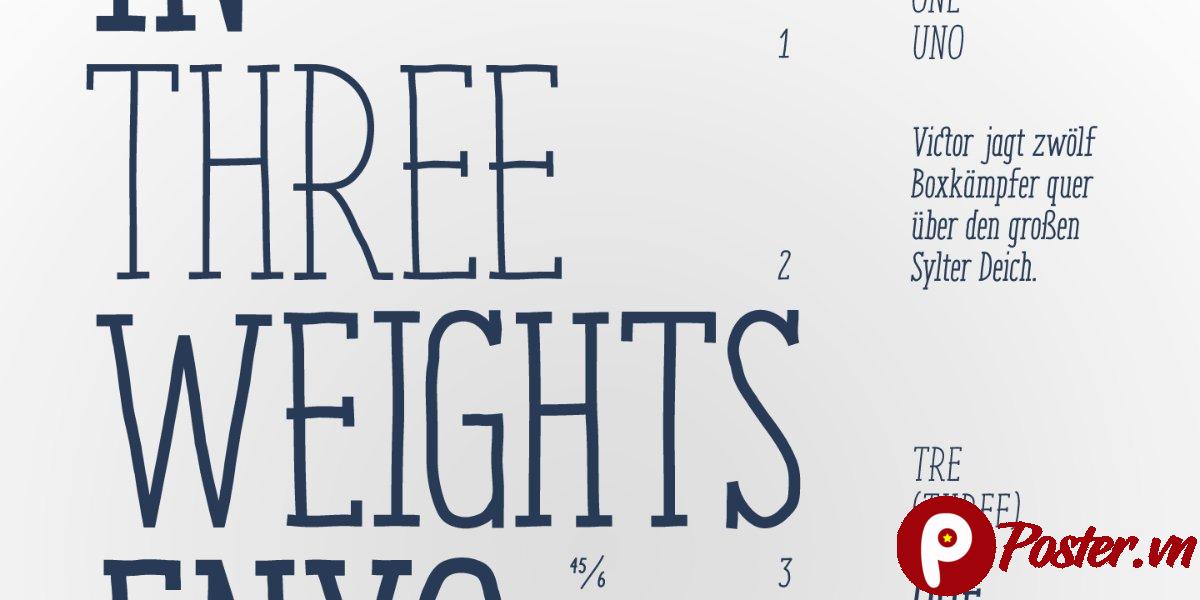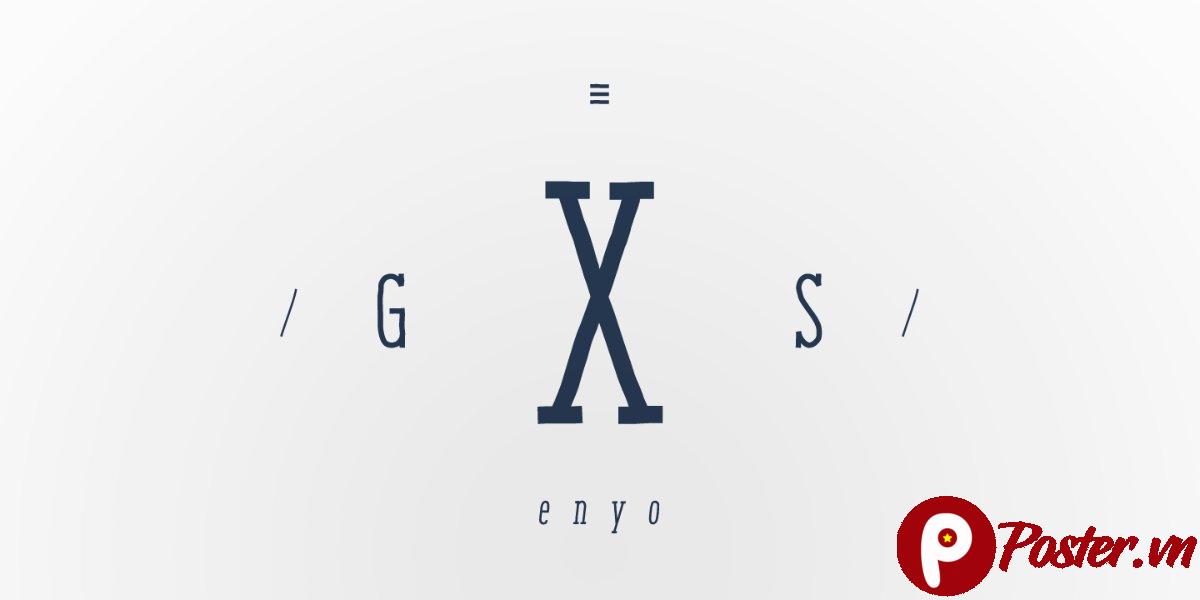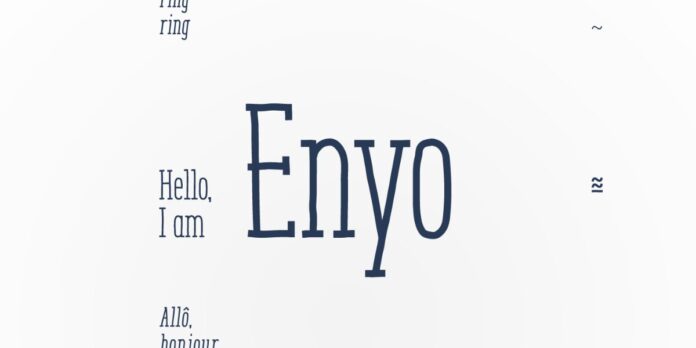
Font Chữ Enyo Đẹp. Khám phá Font Chữ Enyo, một lựa chọn tuyệt vời cho các dự án thiết kế cần sự thanh lịch và rõ ràng. Font này phù hợp cho tiêu đề, logo và nội dung văn bản, mang lại vẻ đẹp tinh tế.
Giới Thiệu Font Chữ Enyo: Sự Kết Hợp Hoàn Hảo Giữa Cổ Điển và Hiện Đại
Font Chữ Enyo là một kiểu chữ serif với nét thanh lịch và rõ ràng, mang đến sự cân bằng giữa vẻ đẹp cổ điển và phong cách hiện đại. Với thiết kế tinh tế, Enyo không chỉ dễ đọc mà còn tạo ấn tượng mạnh mẽ, phù hợp cho nhiều loại hình dự án thiết kế khác nhau. Từ các ấn phẩm in ấn đến thiết kế kỹ thuật số, Enyo luôn là lựa chọn hàng đầu cho những ai tìm kiếm sự chuyên nghiệp và độc đáo.
Đặc Điểm Nổi Bật Của Font Chữ Enyo
Enyo nổi bật với những đặc điểm sau:
- Nét Serif Cổ Điển: Các đường nét serif được thiết kế tỉ mỉ, mang lại cảm giác truyền thống nhưng không kém phần hiện đại.
- Độ Rõ Nét Cao: Dù ở kích thước nhỏ hay lớn, Enyo vẫn giữ được độ rõ nét, giúp người đọc dễ dàng tiếp nhận thông tin.
- Tính Linh Hoạt: Phù hợp cho nhiều mục đích sử dụng, từ tiêu đề, logo, branding đến nội dung văn bản dài.
- Phong Cách Độc Đáo: Enyo mang một phong cách riêng biệt, giúp các thiết kế của bạn trở nên nổi bật và khó quên.
Ứng Dụng Của Font Chữ Enyo Trong Thiết Kế
Font Chữ Enyo có thể được ứng dụng rộng rãi trong nhiều lĩnh vực:
1. Thiết Kế Logo và Branding: Với vẻ ngoài sang trọng và chuyên nghiệp, Enyo là lựa chọn lý tưởng cho các thương hiệu muốn xây dựng hình ảnh đẳng cấp và đáng tin cậy. Sự kết hợp của các nét serif tinh tế giúp logo của bạn trở nên độc đáo và dễ nhận diện.
2. Ấn Phẩm In Ấn: Từ sách, tạp chí, báo cáo đến thiệp mời và danh thiếp, Enyo đều thể hiện sự thanh lịch và dễ đọc. Độ rõ nét cao của font chữ đảm bảo rằng mọi thông tin đều được truyền tải một cách hiệu quả và thẩm mỹ.
3. Thiết Kế Website và Ứng Dụng: Enyo cũng rất phù hợp cho các giao diện người dùng, đặc biệt là các trang web và ứng dụng yêu cầu sự tinh tế và chuyên nghiệp. Font chữ này giúp cải thiện trải nghiệm đọc của người dùng, làm cho nội dung trở nên hấp dẫn hơn.
4. Tiêu Đề và Headline: Với khả năng thu hút sự chú ý, Enyo là một lựa chọn tuyệt vời cho các tiêu đề và headline. Các nét chữ mạnh mẽ nhưng vẫn giữ được sự mềm mại giúp tạo điểm nhấn ấn tượng cho bất kỳ thiết kế nào.
Hướng Dẫn Sử Dụng Font Chữ Enyo Hiệu Quả
Để tận dụng tối đa vẻ đẹp của Font Chữ Enyo, bạn có thể tham khảo một số mẹo sau:
- Kết Hợp Với Font Sans-Serif: Để tạo sự cân bằng và hiện đại, hãy thử kết hợp Enyo (cho tiêu đề) với một font sans-serif đơn giản (cho nội dung).
- Sử Dụng Khoảng Cách Hợp Lý: Đảm bảo khoảng cách giữa các chữ cái và dòng được điều chỉnh hợp lý để tối ưu hóa khả năng đọc.
- Chọn Màu Sắc Phù Hợp: Enyo thường trông đẹp nhất với các màu sắc trầm, cổ điển hoặc các tông màu trung tính, nhưng cũng có thể nổi bật với màu sắc tươi sáng tùy theo ngữ cảnh.
Font Chữ Enyo phù hợp với loại hình thiết kế nào?
Font Chữ Enyo phù hợp với thiết kế logo, branding, ấn phẩm in ấn (sách, tạp chí), tiêu đề, headline và giao diện website/ứng dụng cần sự thanh lịch, chuyên nghiệp.
Làm thế nào để sử dụng Font Chữ Enyo hiệu quả nhất?
Bạn có thể kết hợp Enyo với font sans-serif cho nội dung, điều chỉnh khoảng cách chữ và dòng hợp lý, và chọn màu sắc phù hợp để tối ưu hóa vẻ đẹp của font.